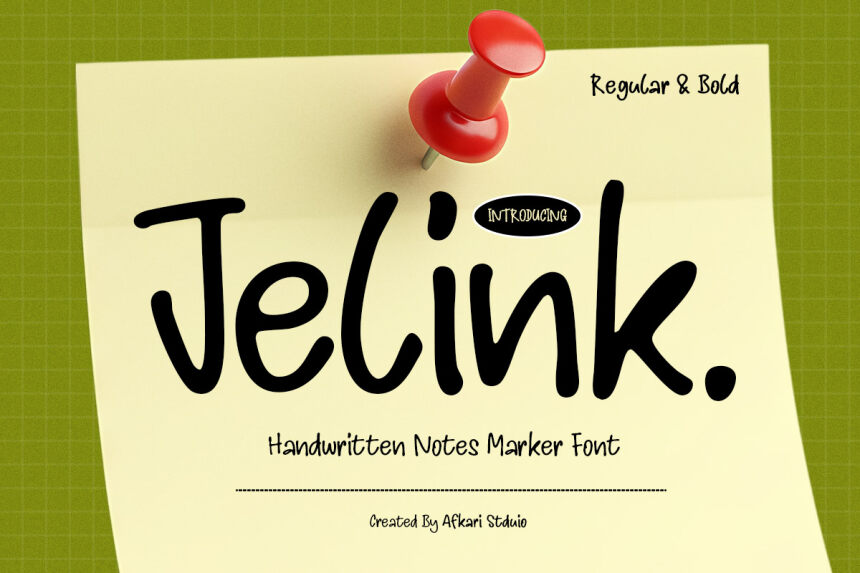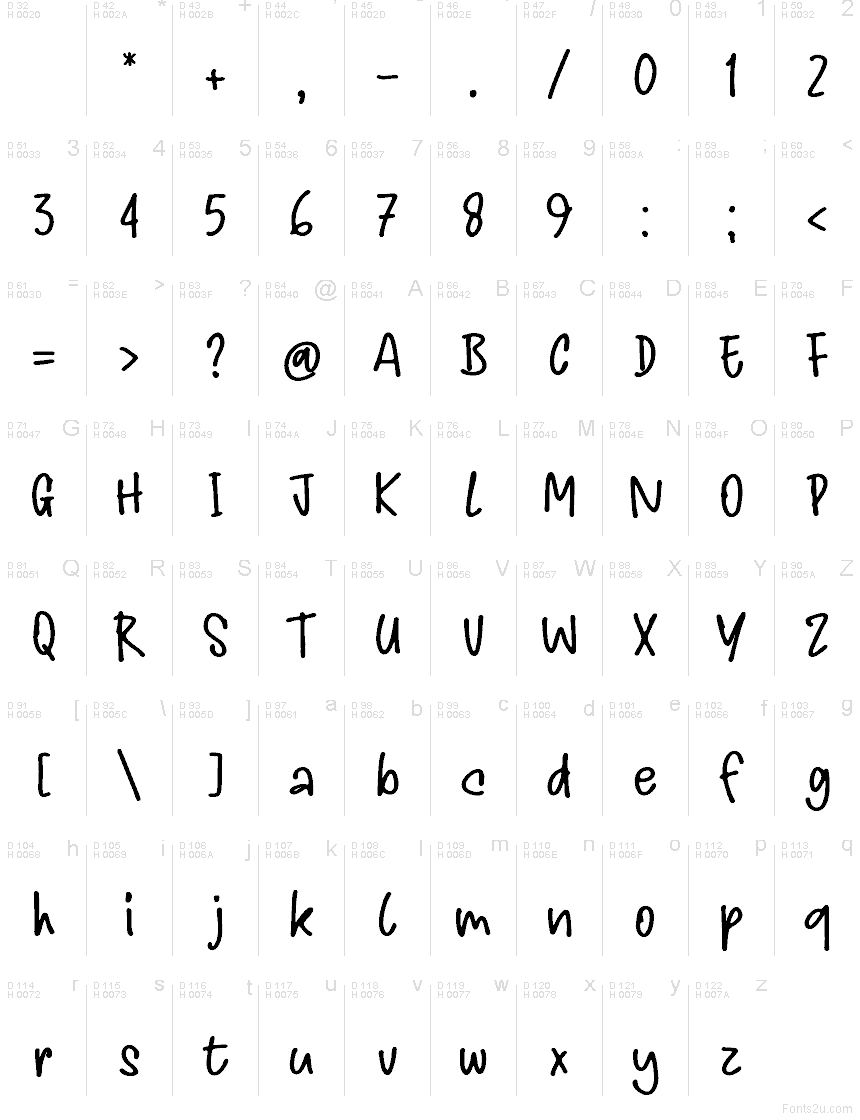
Jelink od Afkari Studio to darmowy krój pisma odręcznego o luźnym, przyjaznym rytmie i naturalnej dynamice, przypominającej pismo grubym markerem. Litery mają zaokrąglone końce, wysokie, zabawne pociągnięcia i lekko nierówne łączenia, co nadaje całości swobodny, osobisty charakter, daleki od sztywnych stylów skryptowych.
Świetnie sprawdza się w projektach opakowań, identyfikacji kawiarni, kartkach okolicznościowych, postach w mediach społecznościowych i krótkich nagłówkach plakatów, gdzie ciepły, ludzki akcent jest ważniejszy niż formalna elegancja. Jako darmowy font, Jelink doskonale nadaje się również do tekstów na okładki i wstępnych szkiców logo, ponieważ jego szerokie kreski i luźny ruch sprawiają, że nawet krótkie słowa nabierają życia.